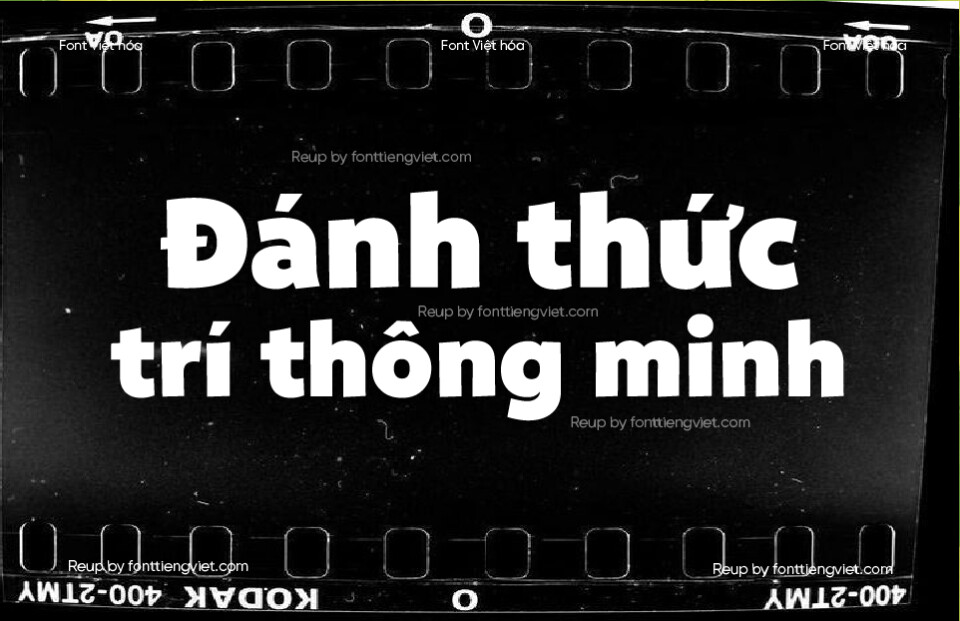
Font Việt hóa UTM Bango Pro
Giới thiệu về Font Việt hóa UTM Bango Pro trong thiết kế
Trong thế giới đồ họa, việc lựa chọn một Font Miễn Phí chất lượng đóng vai trò quan trọng để tạo nên linh hồn cho tác phẩm. Font Việt hóa UTM Bango Pro là một trong những bộ phông chữ nổi bật nhất thuộc hệ thống UTM, được tinh chỉnh kỹ lưỡng để phù hợp với bảng mã tiếng Việt. Với đường nét dày dặn, bo tròn hiện đại và mang phong cách đầy năng lượng, phông chữ này cực kỳ lý tưởng cho các bạn học sinh, sinh viên sử dụng trong các bài thuyết trình hoặc dự án sáng tạo tại nhà trường.
Đặc điểm nổi bật của Font Việt hóa UTM Bango Pro
Điểm mạnh nhất của Font Việt hóa UTM Bango Pro chính là sự cân bằng giữa tính nghệ thuật và khả năng đọc hiểu. Các ký tự được thiết kế với độ tương phản thấp nhưng vẫn giữ được sự rõ nét, giúp nội dung trở nên bắt mắt trên mọi nền tảng từ in ấn đến kỹ thuật số. Đặc biệt, bộ font này đã khắc phục hoàn toàn lỗi dấu tiếng Việt, mang lại trải nghiệm gõ văn bản mượt mà cho người dùng.
Ứng dụng thực tế và cách sử dụng hiệu quả
Bạn có thể sử dụng Font Việt hóa UTM Bango Pro cho các mục đích như thiết kế bìa sách, poster sự kiện trường học hoặc làm tiêu đề video. Để đạt hiệu quả thẩm mỹ cao nhất, hãy kết hợp phông chữ này với các tông màu rực rỡ hoặc pastel nhẹ nhàng. Việc sử dụng đúng cách sẽ giúp thông điệp của bạn trở nên chuyên nghiệp và gần gũi hơn với người xem.